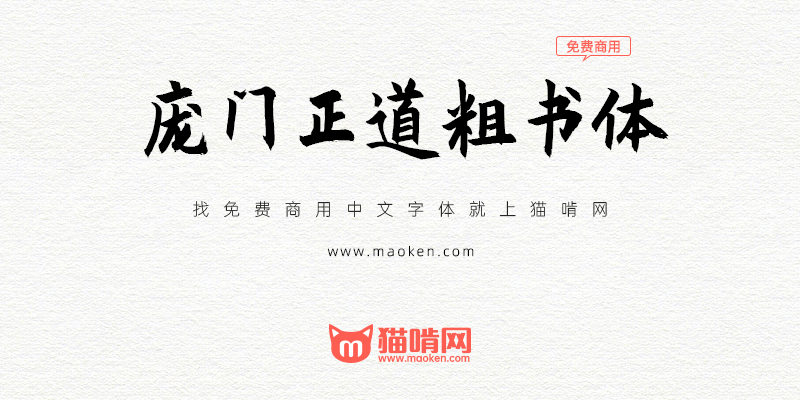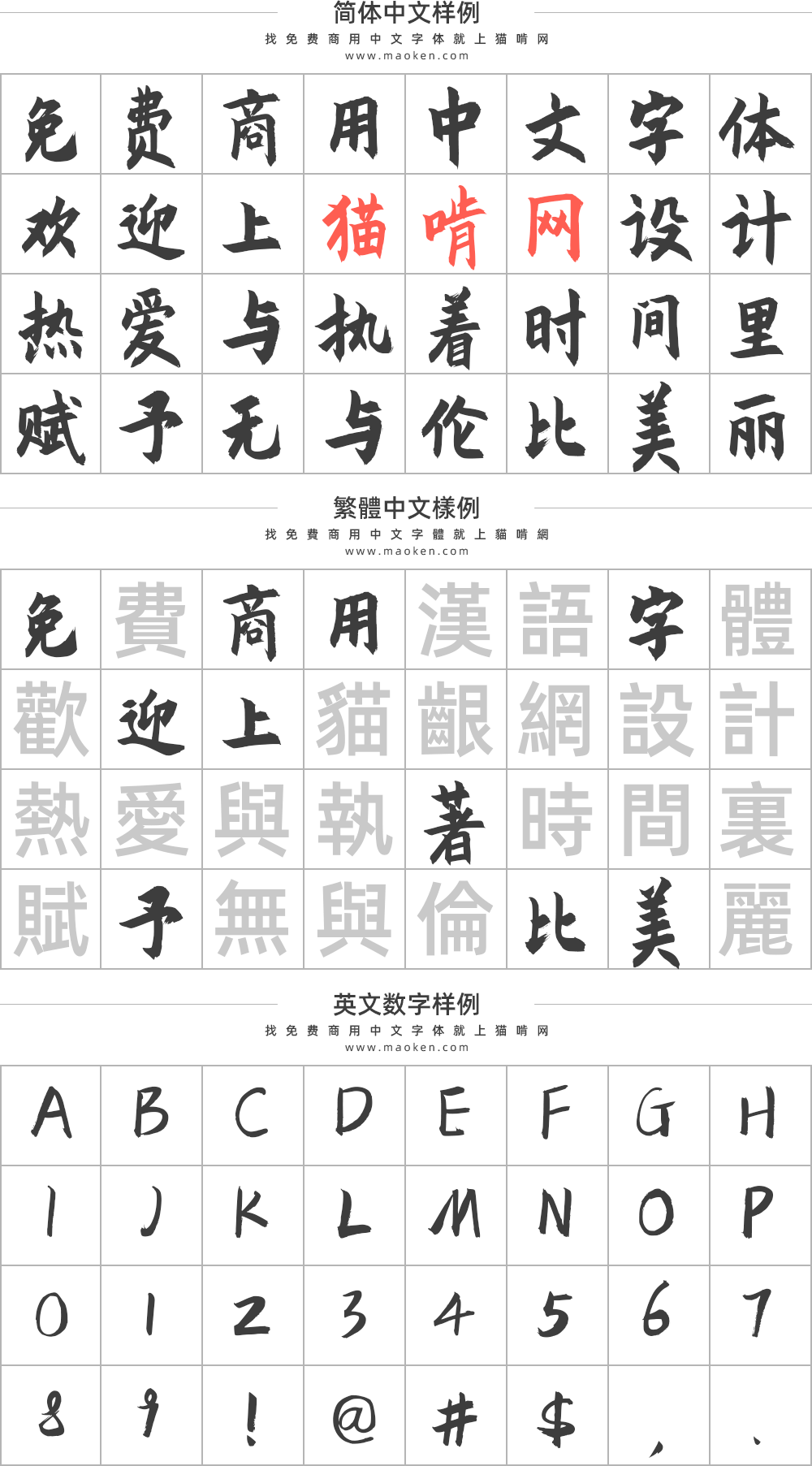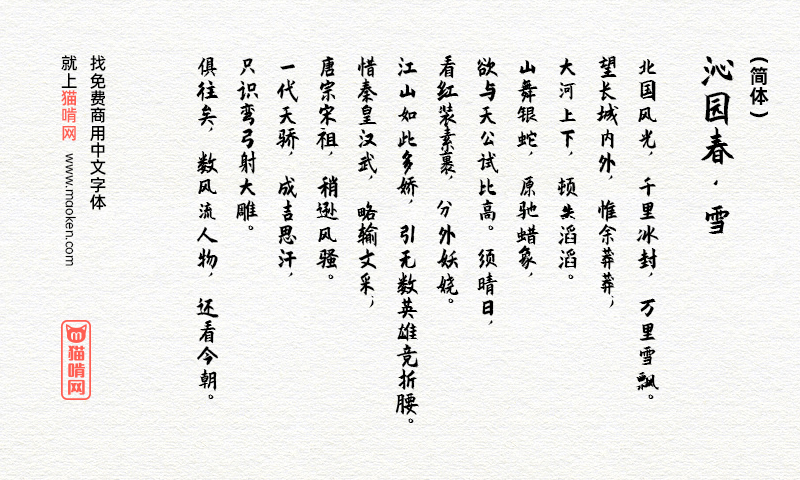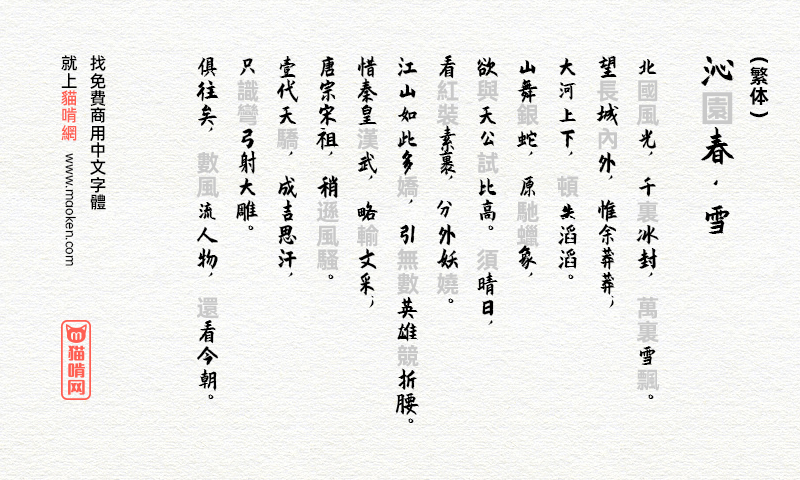
庞门正道粗书体:耗资超过15万元研发 中国首款免费商用毛笔字体
字体作者:车港敏 (中国大陆) 字体字重:1个
字体作者:庞门正道 x 车港敏(中国大陆) 字体字重:1个
庞门正道粗书体发布于2018年12月6日,在日常工作收并不高的艰苦条件下,车港敏同学用了自己业余时间的大半年,完成了一套字库的书写,修改调整等工作。这款字体比预计中的更加受欢迎,就连近段时间的热播剧海报《庆余年》使用的也是庞门正道粗书体。这款字体由《庞门正道》设计公众号以及设计师车港敏耗时9个月耗资超过15万元联合研发。